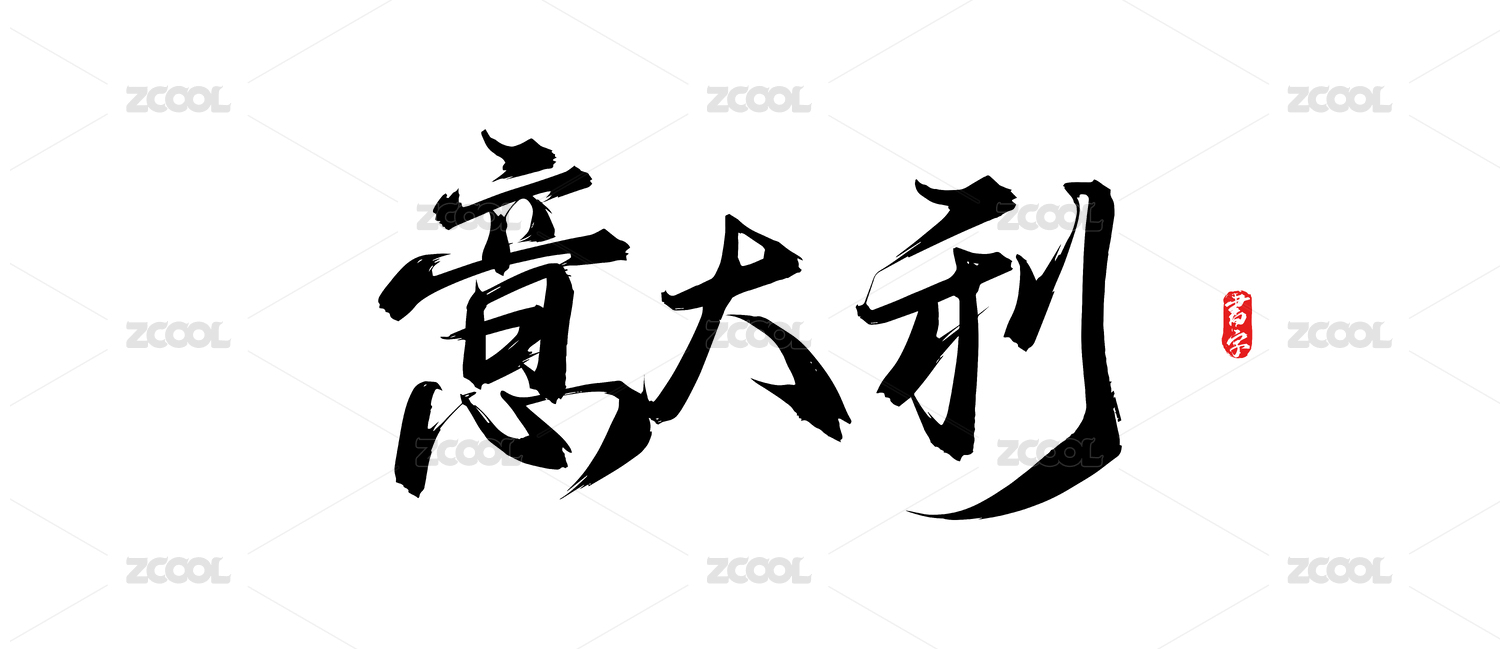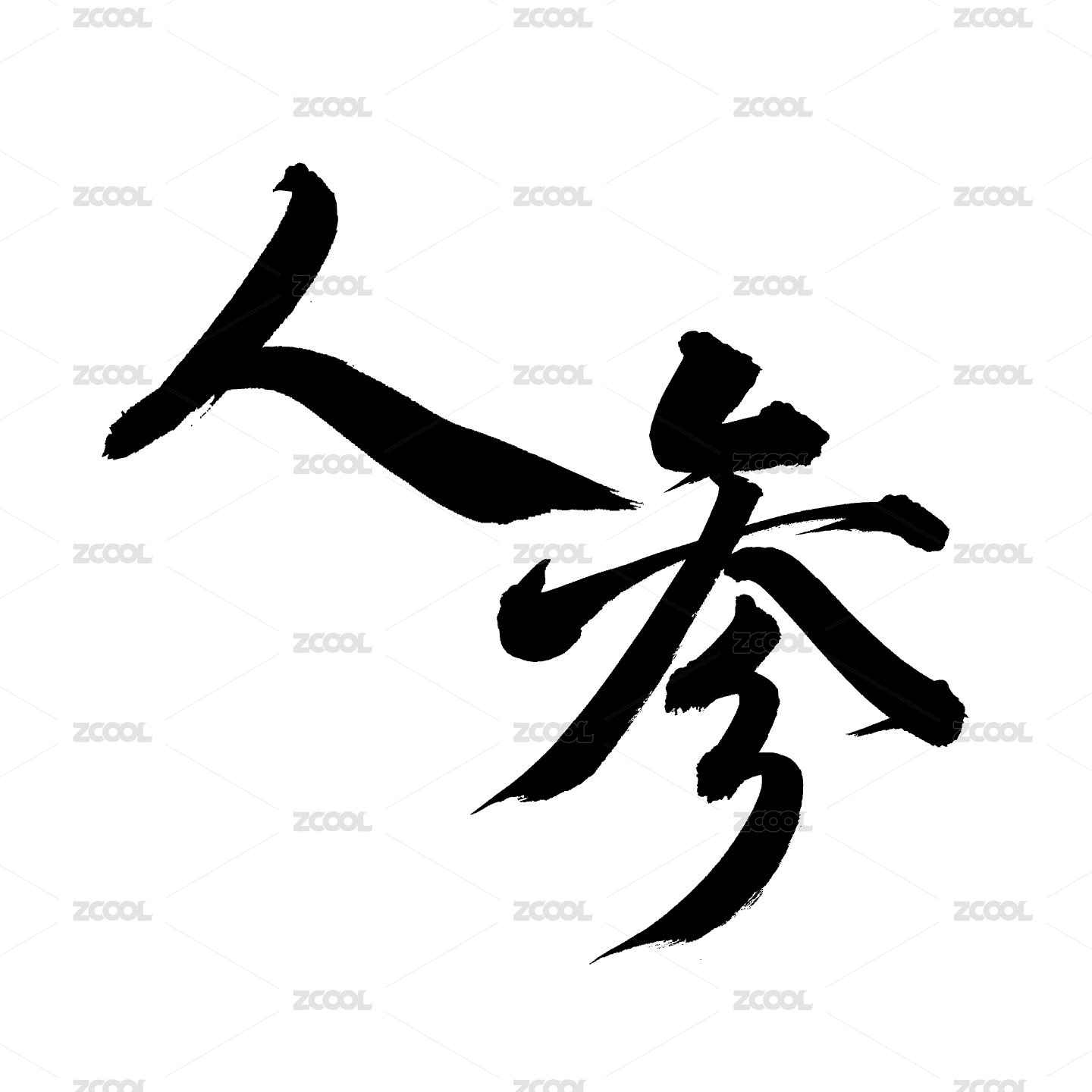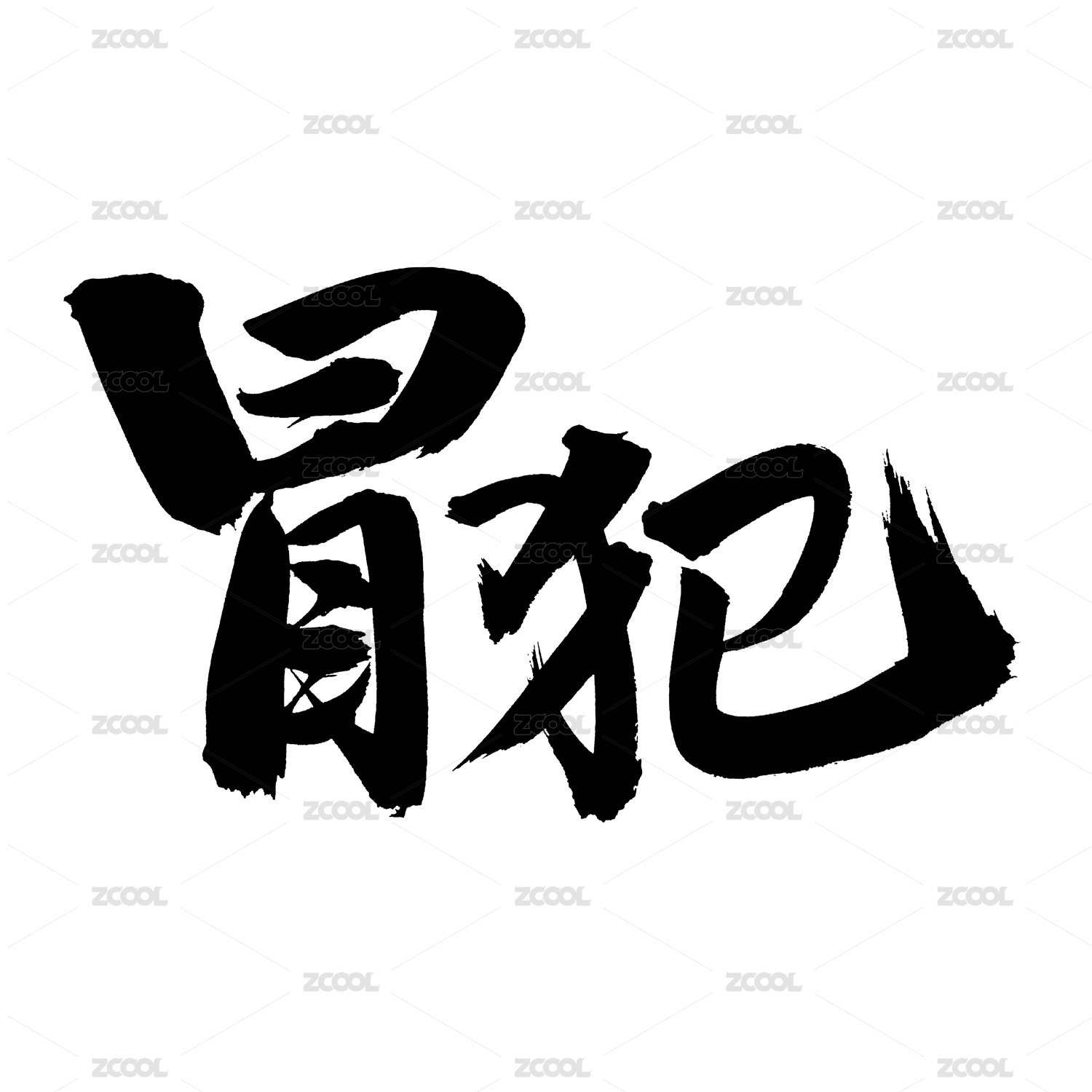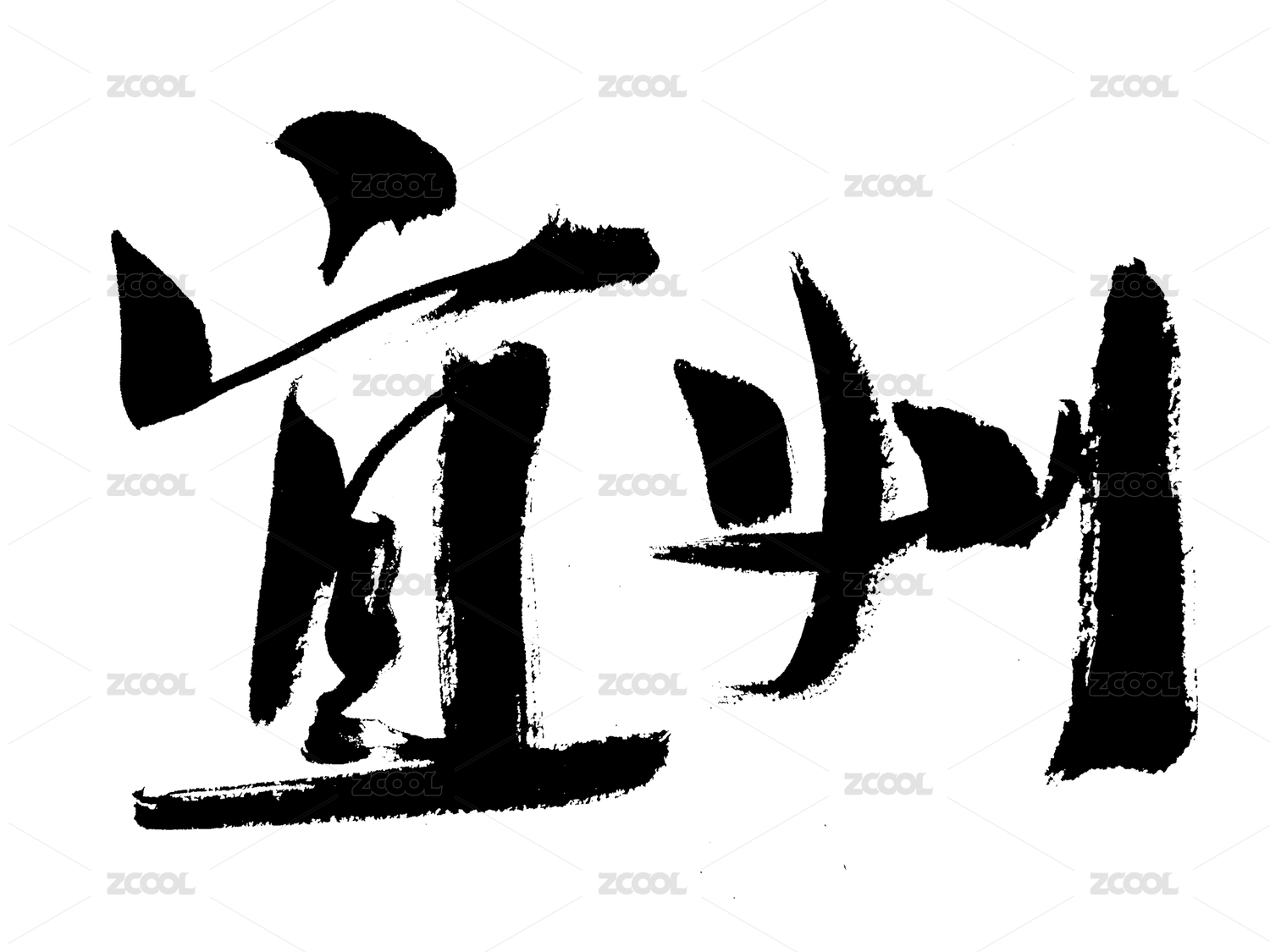
墨浪─刘浪草书作品集
劉浪
意 墨
笔墨之书者,通逸于心间之言,可为古典乐意,墨志相间,畅所以想,由心知而挥墨也,时会新奇之妙,后之而幽境思内。
墨许三生,厚德博学多识,草意在心知,为我之情怀,气魄于年少之气盛,我知书意狂也!
事忆过往在心,吾为长通笔墨达意,真知游目,我心于怀,书客唯心听导,学书之路,任重而道远,乃是一生追求!
意者为我心,博意笔墨之净,作草书者畅怀,后者追与二王,融通而书,张怀之间篆籀之意,由心而书也,不得气势,又取意于黄王之间,空间之错落,线条之潇洒,吾我我心之意墨表达!
元心堂刘浪有感而记之
墨怀相生,元心未变
墨韵之怀在于憶之间,年少时吾好笔墨之意,随之墙面乱涂为童年之趣也,可为心之所向。意在笔先,好古书情游伴年少之时。并印之为我何时之用也。可谓元心之初,笔墨生情寄于时光之间。
元心之意,起为初心之真。真者何乐而不为,由心所畅,游目骋怀于笔墨之间。墨韵相生,意念相境,得之为我失,变之为我知。何时不意笔墨之书,墨怀相生墨在于心,怀在于勤,寄托于笔墨知己。元心末变长叙,感怀助我学书之师者也开之引行书法之间,笔情志通。吾能而立者矣。
知者可以忆昔日,山水之间。通逸雅观墨韵,可悟左右通达,其心尚技于草书之情,墨攻五体为终生,从心通逸,墨志传统,逸雅经典,墨曲悠然自得,会意其乐。
五体书法由见者,吾之篆籀笔法之意,心之所向求学之路为逸庐学书,通我思书之想,可谓善其笔之表达也。
通达进其观也,皆为五体兼养于书,浩然正气目由相生,即为我元心之至,墨怀─忆在远方者之境也。
2021年1月9日元心堂刘浪书于墨志雅斋
对于大草创作空间形式构成延伸的思考
文/刘浪
对于大草的创作,我们看待的角度会影响到我们创作的思路,这一点是非常重要的,最近几年一直在探索大草的创作,对于大草创作的空间形式构成自己有以下几点认识:
一,大草空间形式构成的要素
从书法的传统角度来说,在五体书法篆书,隶书,楷书,行书,草书是在形式空间构成上面是比较有特点的,主要表现在它的点线面之间的构成关系,特别的微妙,我们从平面空间构成的角度来看待的话,我们可以把大草创作的形式看作成一个二维的基本表现,这是创作材料本身的表现主要之一,你是在大草创作当中元素延伸到另外一种维度的表现手法,从二维的空间再延伸到三维的表现,这是大草创作,从传统当中延伸到三维空间构成的比较有特点的构成方式,主要表现有两种常见的横向空间和竖向空间。
(一),横向空间
在草书的横向空间表现是很常见的,其实这是根据汉字的组合结构的关系,横向空间主要表现在左右结构的组合方式,这种组合方式,我们可以在黄庭坚的廉颇蔺相如传,诸上座,看到这种横向空间的构成组合特点,它在左右空间的百度比较大,中间是留白的,从上下左右到中心点轴线的变化,它的空间有向左向右延伸的表现方式,在一件大草作品里面,如果是有横向空间的设计,可以增加整个作品的视觉冲击力和横向,空间的表现,具体的表现,我们可以从字形的笔画特点,如点线面的组合方式来进行笔画的组合,把笔画进行拆分然后再组合,最后得到的是一种自然的构成方式,如果是我们把笔画从左至右的延伸,最后得到的是一个横向的画面,从横向的画面又延伸到上边下面,最后得到的是中心点扩散的点的动态,我们都知道从平面构成的特典中点构成线线构成面面构成一个视觉的整体,这是在大草创作里面横向空间的一大特点,这一点我们可以在大草创作里面大量的使用,可以得到不一样的大草作品的表现形式特点。
(二),竖向空间
竖向空间的表现是我们在大草创作当中经常用到的,也是视觉表现力非常丰富的,它其表现的特点主要是汉字结构组合的上下结构,同时以是一样的从轴线中心的摆动结合横向空间的表现,上下左右形成一点,然后是面进行不同形状的扩散,在不同形状的扩散过程当中得到了相等或不相等的图形,最后形成了一个竖向空间图形,这一点我们也可以从黄庭坚的廉颇蔺相如传得到一个结论,上下结构字的特点是气势宏博有助于在整篇作品的气象的表现,可以拉开上下左右直接拥挤而不聚散的结构问题,特别是我们在创作8尺6尺整张这样大尺寸的作品,我们需要这样的空间摆动,竖向空间的摆动特点是动态和静态之间的一种融合,他能够在上下形成一种动态,也能够在轴线的摆动形成一种静态,所以可以充分地体现我们作品的动静结合的关系,最终形成不一样的形状,块面,点线面之间的三角形空间构成特点,其主要的关系是从大到小从小到大的大小延伸,
二,空间形状的变化关系
空间形状是我们在大草创作里面特别重要的一个章法设计方式,不管我们书写的是汉字还是画的是图形,其实特点都是点线面的构成组合方式,我们从平面构成原理的角度进行看待的话,在不同形状的构成方式当中,它会呈现不同的视觉表现以及点线面的视觉冲击力,这一点我们也是可以在古人的作品里面可以清楚的看到,比如说王羲之的圣教序里面就有很多字形,块面行中的变化,这种变化在点线面的组合方式当中把形状形成了一种组合方式,比如说把三角形,正方形,四边形,菱形,等等不一样的形状组合成一个整体,它就形成了不一样的视觉表现力。
(一),三角形的形状变化
三角形的形状变化,其主要的特点是由小慢慢的透视到大的层面,那么在我们草书作品当中,也是经常用到的,比如说,我们从比较小的字延伸到比较大的字,它就是这种由远到近的一种透视原理,反过来如果是把三角形旋转,90度的话,它的形状就会随之而相反,以前是从小变大的,现在是从大变小,形成一种上下互补的菱形空间变化关系,同样的在三角形的变化过程当中以示围绕横向空间竖向空间来进行变化的,这种变化已是汉字结构的特点,上下左右之间的变化关系,
(二),正方形的形状表现
从三角形的延伸再到正方形的表现,它是一种相互融合的过程,同时也是在汉字组合过程当中,一种由点到线到面的空间构成方式,其正方形主要的空间构成特点是上下左右沿着轴线的变化形成一种局部的空间表现,这种表现当中,在我们写整张作品当中,第3行最后结尾的时候可以用到这种组合方式,因为他到最后可以形成一定的块面感,让点线面之间的表现,更加的强烈对比,更加的协调。